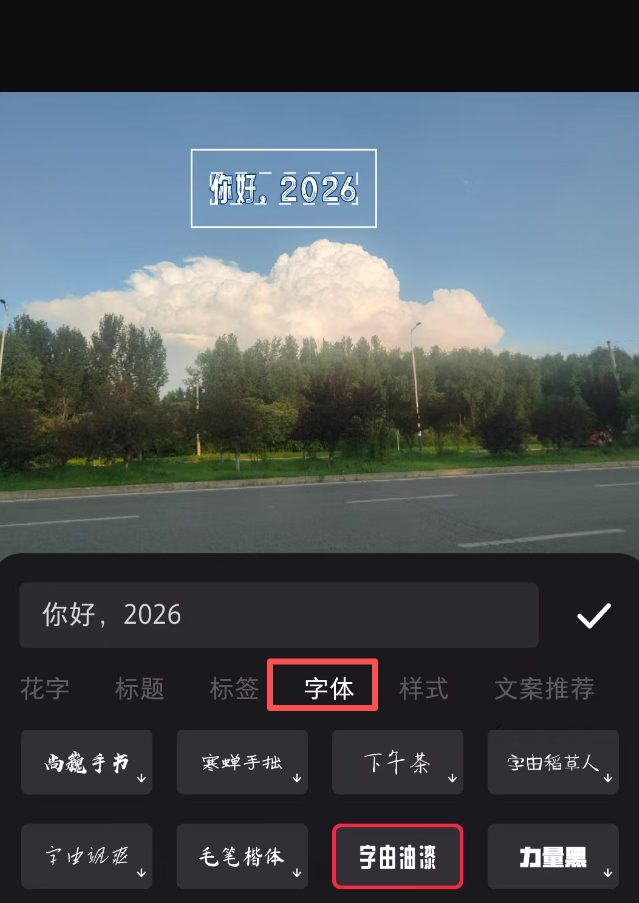
字由嵌入式字体合作案例,内容社区产品 - 小红书
小红书这种内容社区类产品,字体是否匹配平台的调性是非常重要的,所以,字由嵌入式字体的方式更侧重于情感契合与风格化表达。
小红书作为年轻人分享生活的社交平台,对于字体的要求也是相对轻松、艺术类的风格。但作为小红书平台来说,自己从零原创字体肯定是不现实的。字由嵌入式字体是非常简单高效的解决方式。
字由的字体是如何嵌入到小红书的
字由精心筛选并提供了多款契合平台“生活美学”、“真实分享”调性的字体入驻小红书。这些字体视觉上更具手写感、松弛感与亲和力,完美适配日常Vlog、好物笔记等内容形式,从视觉设计层面帮助用户和平台提升内容的质感与辨识度。
如何在小红书使用这些字体
当你使用小红书直接进行内容创作时,你可以在后台中的字体中,进行筛选。
除了小红书中嵌入的字体,字由拥有几百款原创的字体,平台可以根据需求,进行增加。
内容社区产品做字体嵌入有哪些好处
让用户使用后台进行内容创作
我们知道,除了在小红书后台进行内容创作外,还有很多图片、视频制作工具。平台做了字体嵌入后,创作者无需离开当前软件去外部寻找、下载、安装字体,一切在编辑器内完成,极大提升创作效率。
节省字体原创成本
作为小红书这种内容平台,不用非得要原创字体资源,劳神费力。在字由丰富的字体库中直接筛选,符合平台特点、调性的字体。
内容社区产品字体嵌入流程
确定使用场景
确定字体使用在 UI界面、编辑器实时渲染、导出文件(图片/视频/PDF)、云渲染等场景。
确定嵌入字体
基于品牌调性与场景需求,推荐适配的字体组合(基础库+精选库+定制字)。
提供线上预览Demo,支持多款字体对比。
字体上线
客户可根据自身产品节奏安排上线时间,字由字库提供必要的上线前验证支持,确保字体在目标环境中正常呈现。
为什么选择字由做字体嵌入
海量正版多语种字库,支持定制开发
完整覆盖简体、繁体、中日韩、拉丁文字符体系,提供专属定制字体研发服务,充分适配多语言产品、多元化商业场景使用需求。
专业级精工出品,跨媒介渲染稳定
市面多数新兴字库普遍存在笔画精度不足、字符缺失、多设备显示色差等缺陷。本平台字体采用标准化专业设计流程,搭配全维度质检管控,保证字体在网页、APP、印刷物料等各类媒介中显示清晰、字形统一。